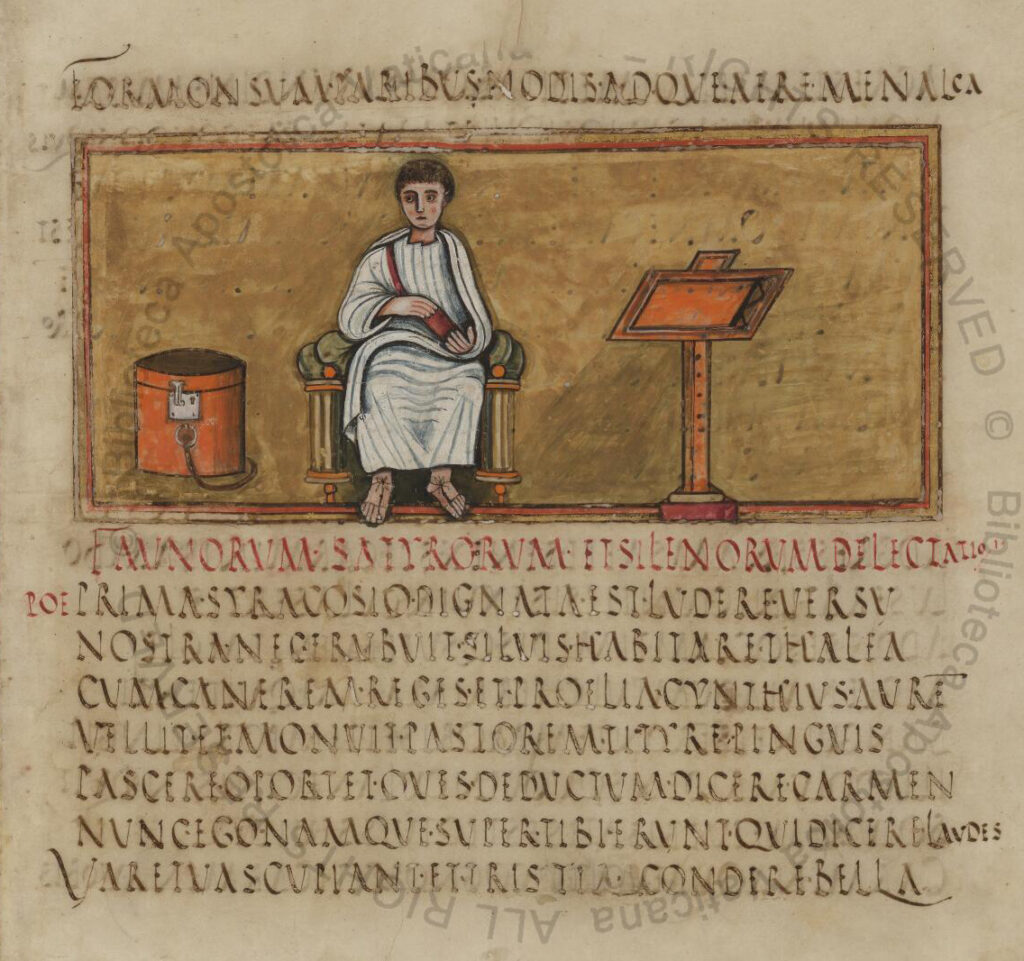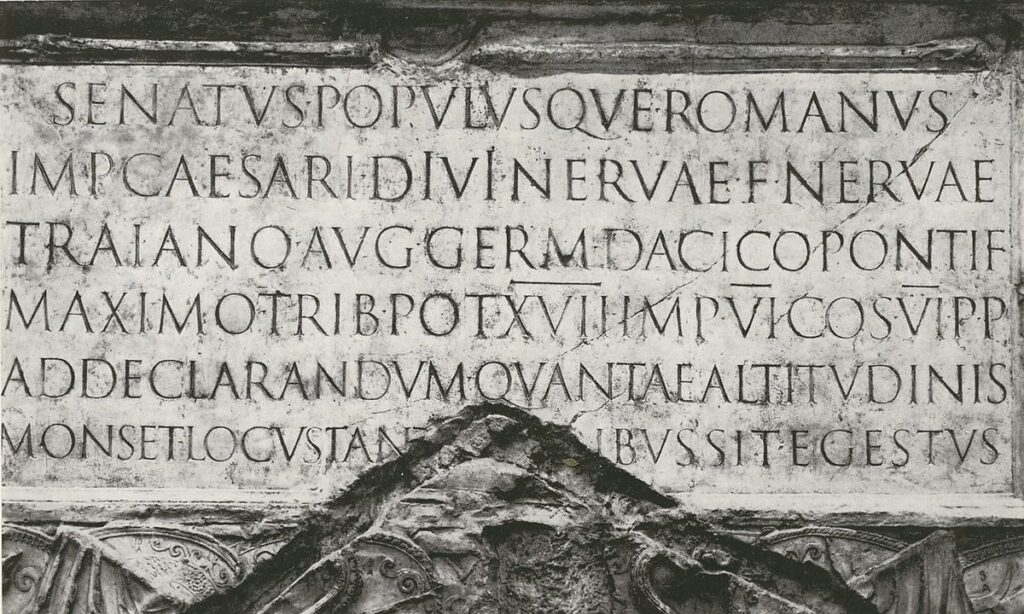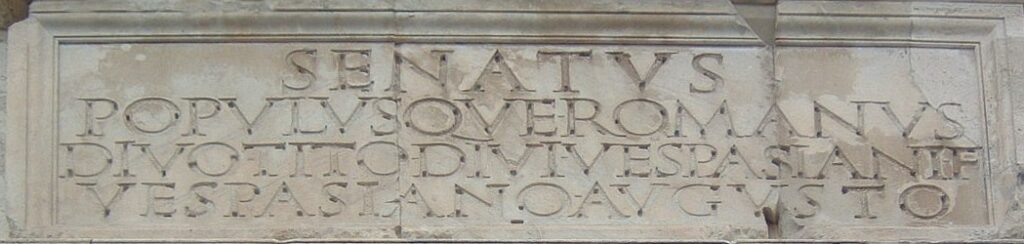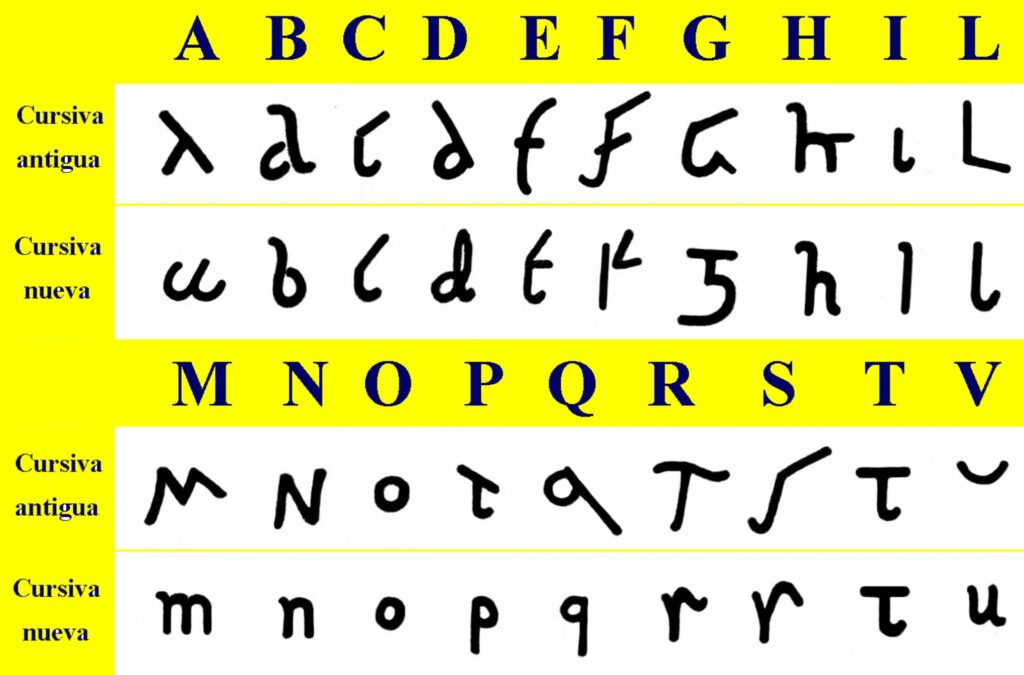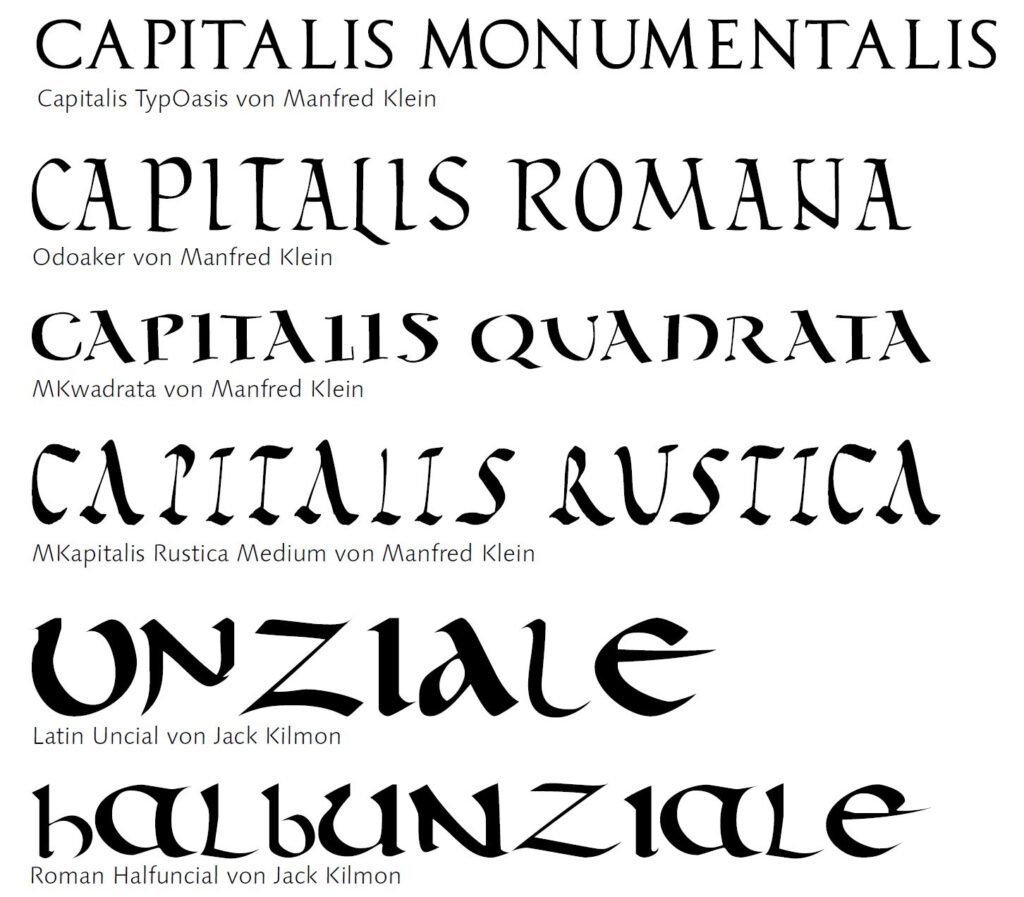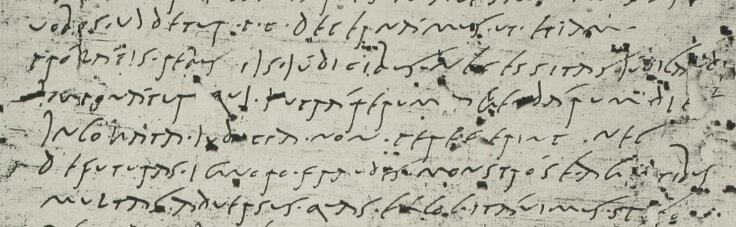
100 v. Chr.
Nach der Übernahme des das phönizische Alphabetes und Anpassung durch die Griechen gelangte das Alphabet nach Italien, wo die Urschrift der lateinischen Schriften entstand: die Römische Kapitalis oder Capitalis Romana. Diese Großbuchstabenschrift mit Querstrichen an den Senkrechten – Vorläufer der Serifen – wurde in Stein gemeißelt und eignete sich kaum zum Schreiben. Die geschriebene Variante, die Capitalis Quadrata, orientierte sich in Abständen, Proportionen und Formen am Goldenen Schnitt. Aufgrund des hohen Schreibaufwands diente sie vor allem für besonders anspruchsvolle Texte.
Mit Feder und Pergament sowie dem Bedürfnis nach schnellerem Schreiben entwickelten sich daraus die Capitalis Rustica und weitere kursive Ableitungen.
Der Untergang des Römischen Reiches führte zum Verfall der Schriftkultur. Kirche und Gelehrte behielten ihren Einfluss auf die Schriften, lehnten aber das »heidnische Rom« ab und damit auch dessen Schriften. Aus den Formen der römischen Buchschriften entstand stattdessen die Unziale, eine rundere Schrift, die erstmals das Zwei-Linien-Prinzip verließ: Kleinbuchstaben mit Ober- und Unterlängen wurden deutlich erkennbar. Darauf aufbauend entstand die Halbunziale, die bereits eine echte Vier-Linien-Schrift darstellt.
Capitalis Monumentalis
Als Vorbild aller Antiquaschriften diente die Capitalis Monumentalis. Ihre geometrischen Grundformen – Kreis und Quadrat – wurden mit Hammer und Meißel in Stein gehauen. Die späteren Serifen entstanden vermutlich durch das Ansetzen des Meißels.